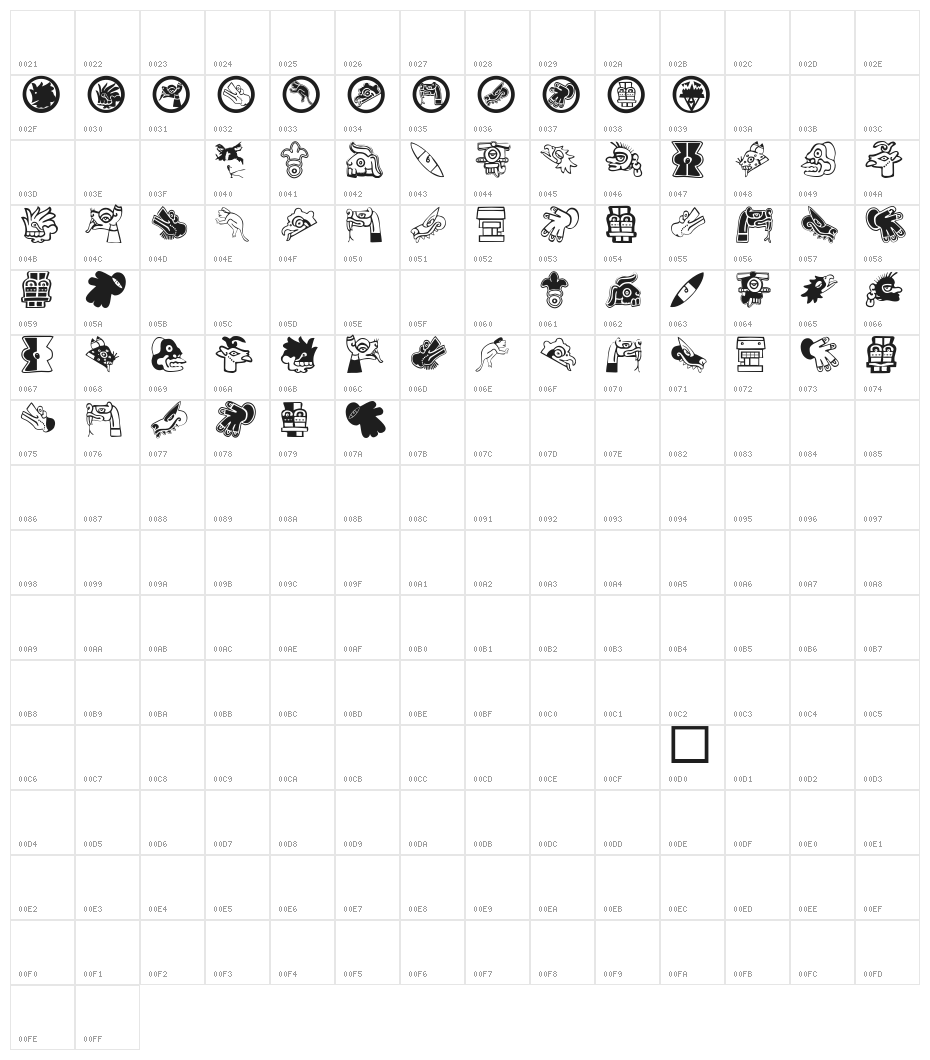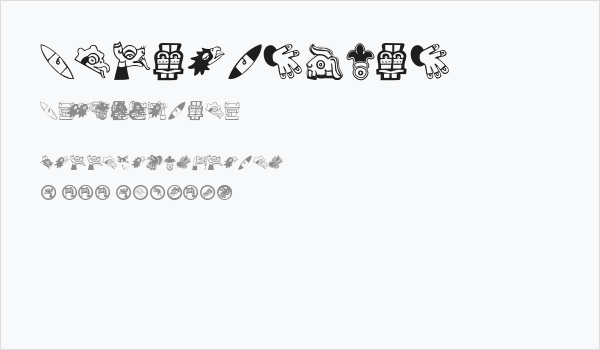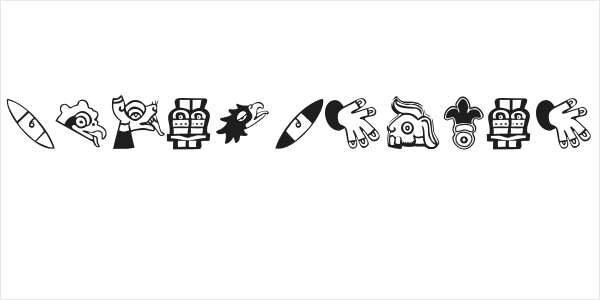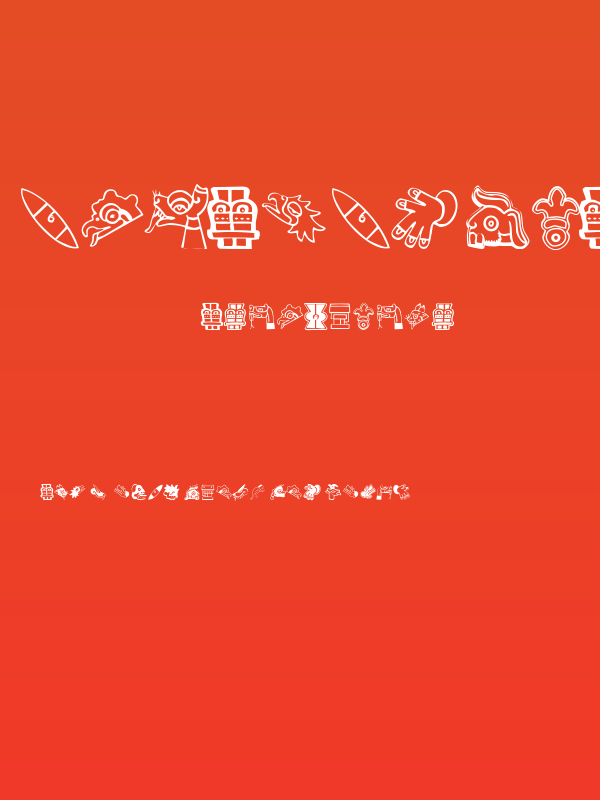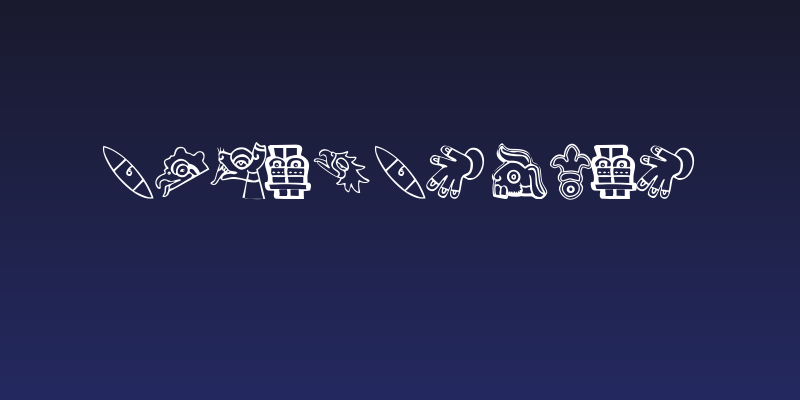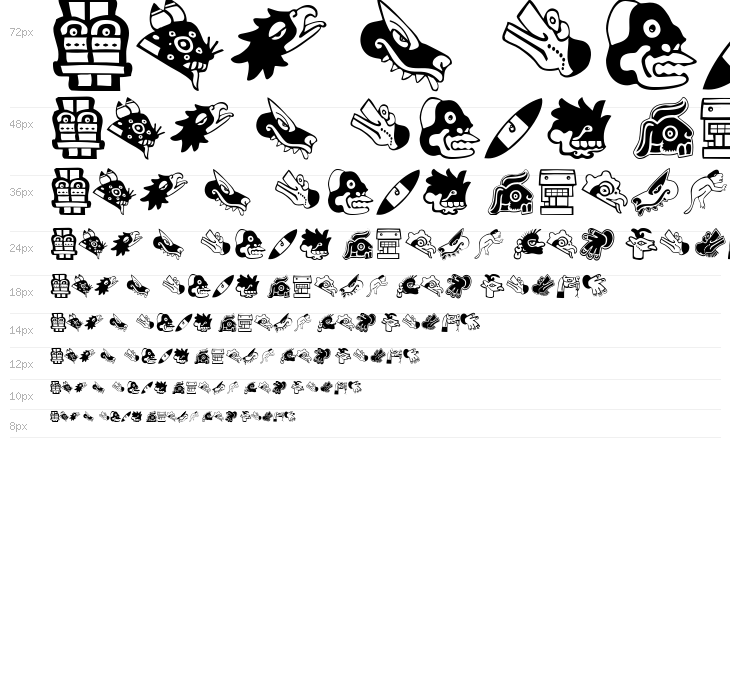
ColtecsBats Font
| Stile generale | Decorative, Ancient, Cultural |
| Caso d'uso | Logos, Headlines, Posters, Themed graphics |
| Progetti proposti | Cultural posters, themed event invitations, educational materials about ancient civilizations, museum displays, creative branding for historical or cultural projects. |